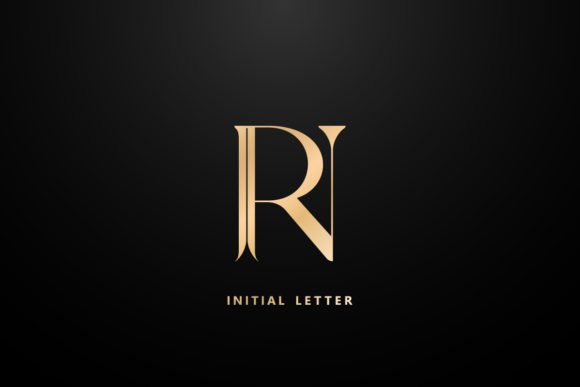
RN Monogram Lettering Fonts with Modern
Die richtigen Designelemente zu finden, kann eine Herausforderung sein, aber RN Monogram Lettering Fonts with Modern bietet eine außergewöhnliche Sammlung, die Ihre Arbeit sofort aufwertet.
Egal, ob Sie POD-Produkte (Print on Demand), Hochzeitseinladungen oder Social-Media-Grafiken erstellen, RN Monogram Lettering Fonts with Modern ist die ideale Wahl.